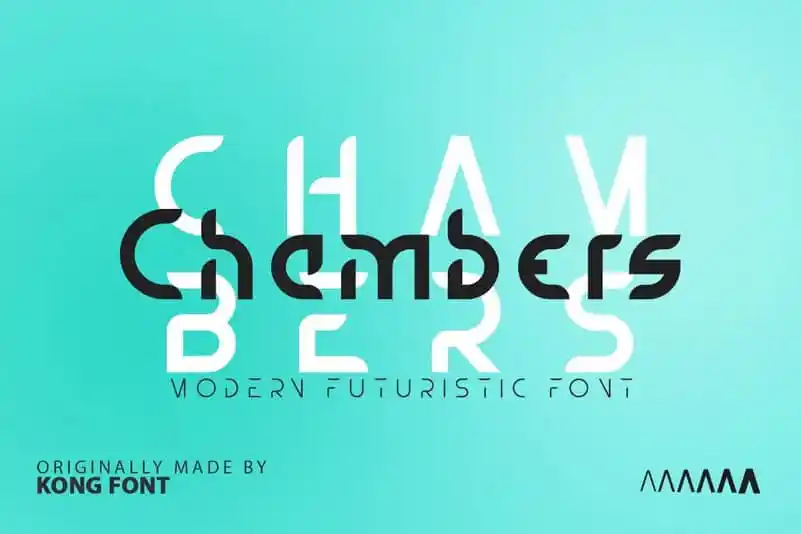
Chambers Display Font – Download Grátis
A Chambers Display Font é uma elegante tipografia sans-serif que combina a sofisticação clássica com o modernismo intrínseco. Desenvolvida pelo designer Kong Font, esta fonte oferece um equilíbrio perfeito entre tradicional e contemporâneo, tornando-se uma escolha ideal para uma variedade de projetos. Perfeita tanto para aplicações visuais formais como para ambientes criativos, a Chambers Display se destaca em áreas que exigem um toque especial de design. É perfeita para aplicar em logotipos e marcas, mensagens de branding inovadoras, fotografias assinadas ou mesmo para criar cartões de visita, convites de casamento, textos de citações e até as cabeças de postagens em blogs e páginas web. Ela também encaixa-se perfeitamente no design de materiais promocionais, como anúncios e cartões-postais. A Chambers Display é um recurso versátil que não apenas dá uma aparência única a seu projeto, mas também contribui para a coesão do design em qualquer ambiente onde ela seja usada. Seja ele uma fonte de referência para designers gráficos ou simplesmente alguém interessado em recursos digitais, Chambers Display é um investimento valioso no mundo dos projetos visuais. Suas linhas modernas e seu estilo sofisticado tornam a Chambers Display Font uma escolha inteligente para quem busca a perfeição em cada projeto.